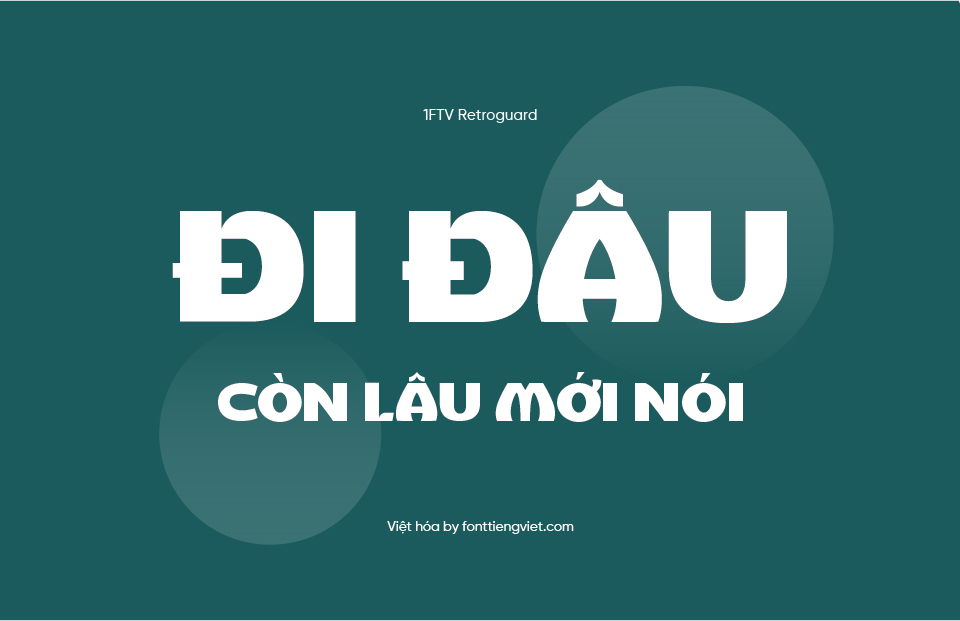
Font Việt hóa 1FTV Retroguard
Giới thiệu về Font Việt hóa 1FTV Retroguard
Trong thế giới đồ họa hiện đại, việc tìm kiếm một bộ Font Miễn Phí mang đậm phong cách cổ điển nhưng vẫn đảm bảo tính ứng dụng cao là điều không hề dễ dàng. Font Việt hóa 1FTV Retroguard chính là câu trả lời hoàn hảo cho những ai yêu thích vẻ đẹp retro của thập niên 80. Đây là bộ font được tinh chỉnh kỹ lưỡng, hỗ trợ đầy đủ bộ gõ tiếng Việt, giúp các bạn học sinh và giáo viên dễ dàng tạo ra những bài thuyết trình hay ấn phẩm truyền thông học đường bắt mắt. Với đường nét mạnh mẽ và dứt khoát, bộ chữ này mang lại cảm giác hoài niệm nhưng không kém phần chuyên nghiệp.
Ưu điểm nổi bật của Font Việt hóa 1FTV Retroguard
Phong cách thiết kế độc đáo
Font Việt hóa 1FTV Retroguard sở hữu các đường nét dày dặn, mô phỏng các bảng hiệu quảng cáo cũ, tạo nên sức hút thị giác cực lớn. Điểm đặc biệt của nó là sự cân bằng giữa yếu tố nghệ thuật và khả năng đọc, giúp nội dung luôn hiển thị rõ ràng trên cả màn hình máy tính lẫn bản in. Các bạn có thể sử dụng font này để thiết kế tiêu đề báo tường, băng rôn sự kiện hoặc trang trí bìa sách vở.
Cách ứng dụng Font Việt hóa 1FTV Retroguard hiệu quả
Để tận dụng tối đa vẻ đẹp của Font Việt hóa 1FTV Retroguard, bạn nên kết hợp với các gam màu trầm hoặc màu pastel đặc trưng của phong cách vintage. Đừng quên sử dụng nó cho các tiêu đề chính (Heading) để tạo điểm nhấn, tránh dùng cho các đoạn văn dài để đảm bảo người xem không bị mỏi mắt. Đây thực sự là lựa chọn lý tưởng để làm mới các dự án học tập hàng ngày.